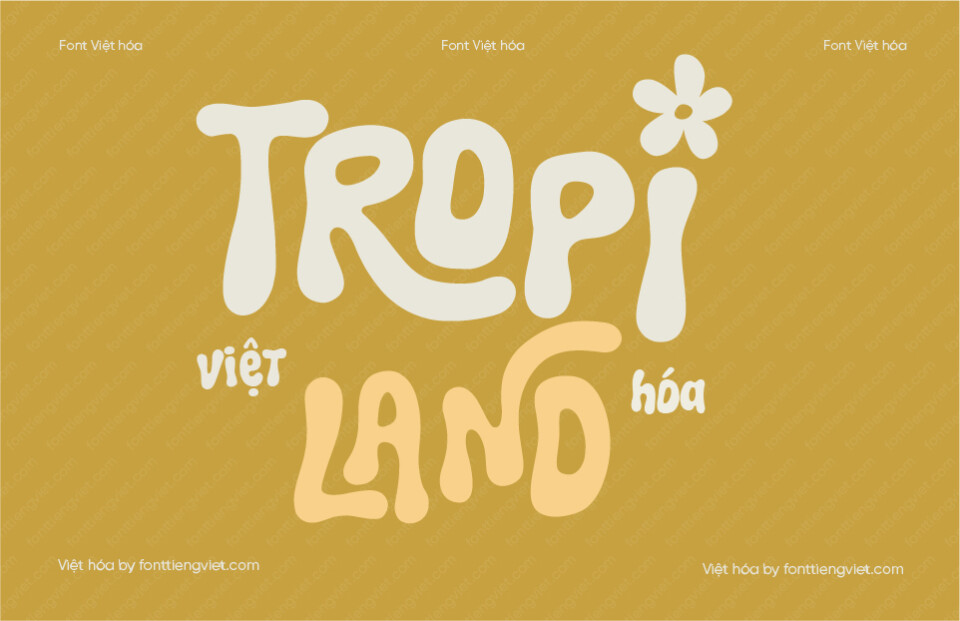
Font Việt hóa 1FTV VIP Tropi Land
Giới thiệu về bộ Font Việt hóa 1FTV VIP Tropi Land
Trong thế giới đồ họa hiện đại, việc lựa chọn một Font Miễn Phí chất lượng là yếu tố then chốt để tạo nên sự khác biệt. Font Việt hóa 1FTV VIP Tropi Land nổi bật như một làn gió mới mang phong cách nhiệt đới đầy phóng khoáng. Đây là bộ phông chữ được tinh chỉnh kỹ lưỡng, hỗ trợ đầy đủ bảng mã tiếng Việt, giúp người dùng không còn lo lắng về lỗi hiển thị dấu khi thiết kế các ấn phẩm truyền thông hay tài liệu giảng dạy. Với đường nét mềm mại nhưng vẫn giữ được sự chắc chắn, bộ font này cực kỳ phù hợp cho các tiêu đề lớn, banner quảng cáo hoặc các dự án sáng tạo đòi hỏi tính thẩm mỹ cao và sự gần gũi với thiên nhiên.
Đặc điểm nổi bật của Font Việt hóa 1FTV VIP Tropi Land
Phong cách thiết kế độc đáo và linh hoạt
Font Việt hóa 1FTV VIP Tropi Land sở hữu cấu trúc chữ độc đáo, mang lại cảm giác vui tươi và tràn đầy năng lượng. Các nghệ sĩ thiết kế đã lồng ghép khéo léo những đường cong tinh tế vào từng ký tự, tạo nên một tổng thể hài hòa và bắt mắt. Đặc biệt, bộ font này rất phù hợp với môi trường học đường, giúp các em học sinh dễ dàng tiếp cận nội dung thông qua những hình ảnh chữ viết sinh động. Bạn có thể sử dụng nó để làm bìa sách, thiệp mời hoặc trang trí các góc học tập thêm phần thú vị.
Khả năng ứng dụng đa dạng trong thực tế
Không chỉ giới hạn trong lĩnh vực quảng cáo, Font Việt hóa 1FTV VIP Tropi Land còn được ứng dụng rộng rãi trong các video blog, trang web cá nhân và ứng dụng di động. Sự tương thích cao giữa các phần mềm đồ họa như Photoshop hay Illustrator giúp quá trình làm việc trở nên mượt mà hơn bao giờ hết. Đây thực sự là một công cụ hỗ trợ đắc lực cho những ai đang tìm kiếm sự chuyên nghiệp nhưng vẫn muốn giữ lại nét cá tính riêng biệt.
Kết luận và hướng dẫn sử dụng font hiệu quả